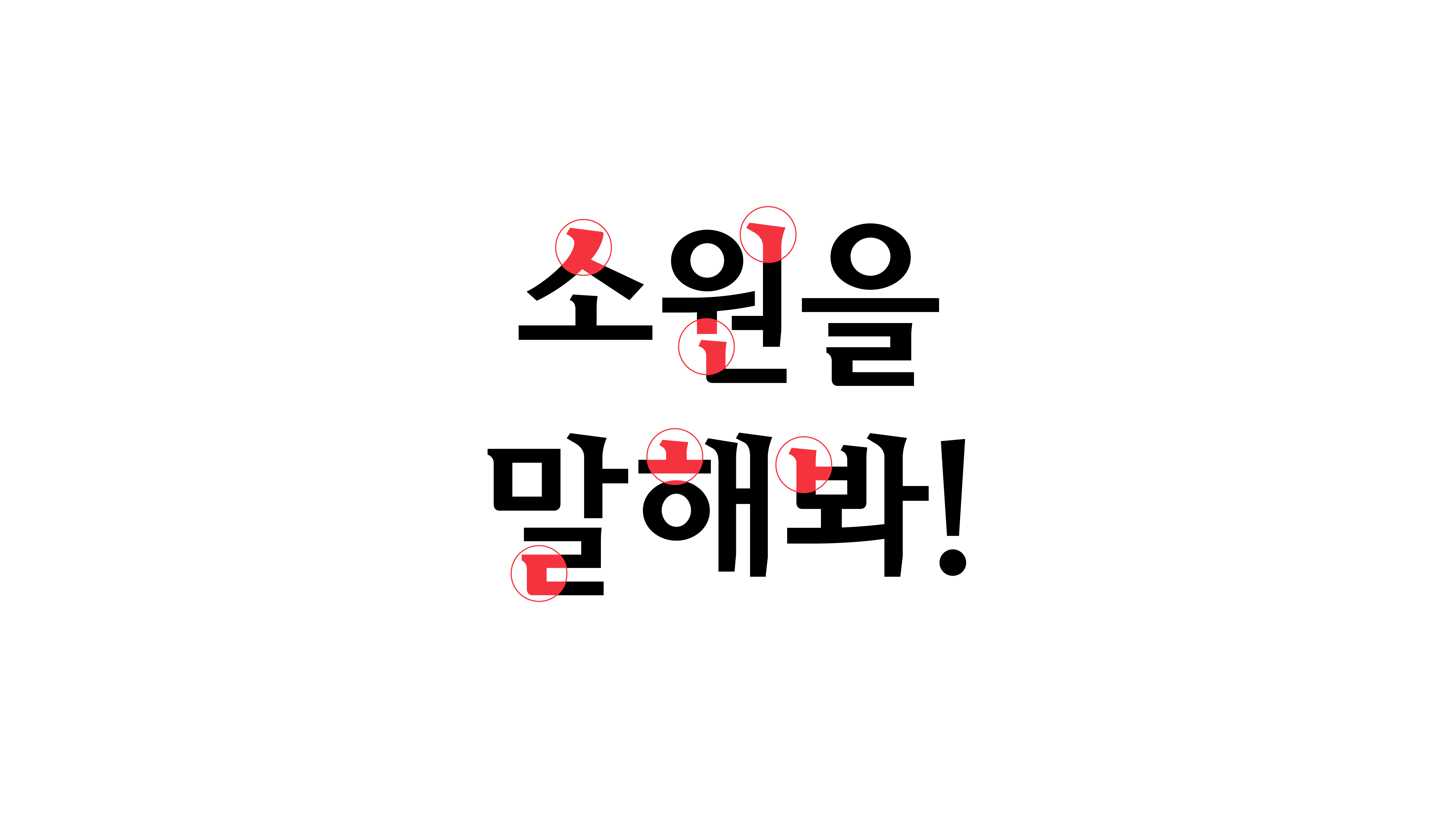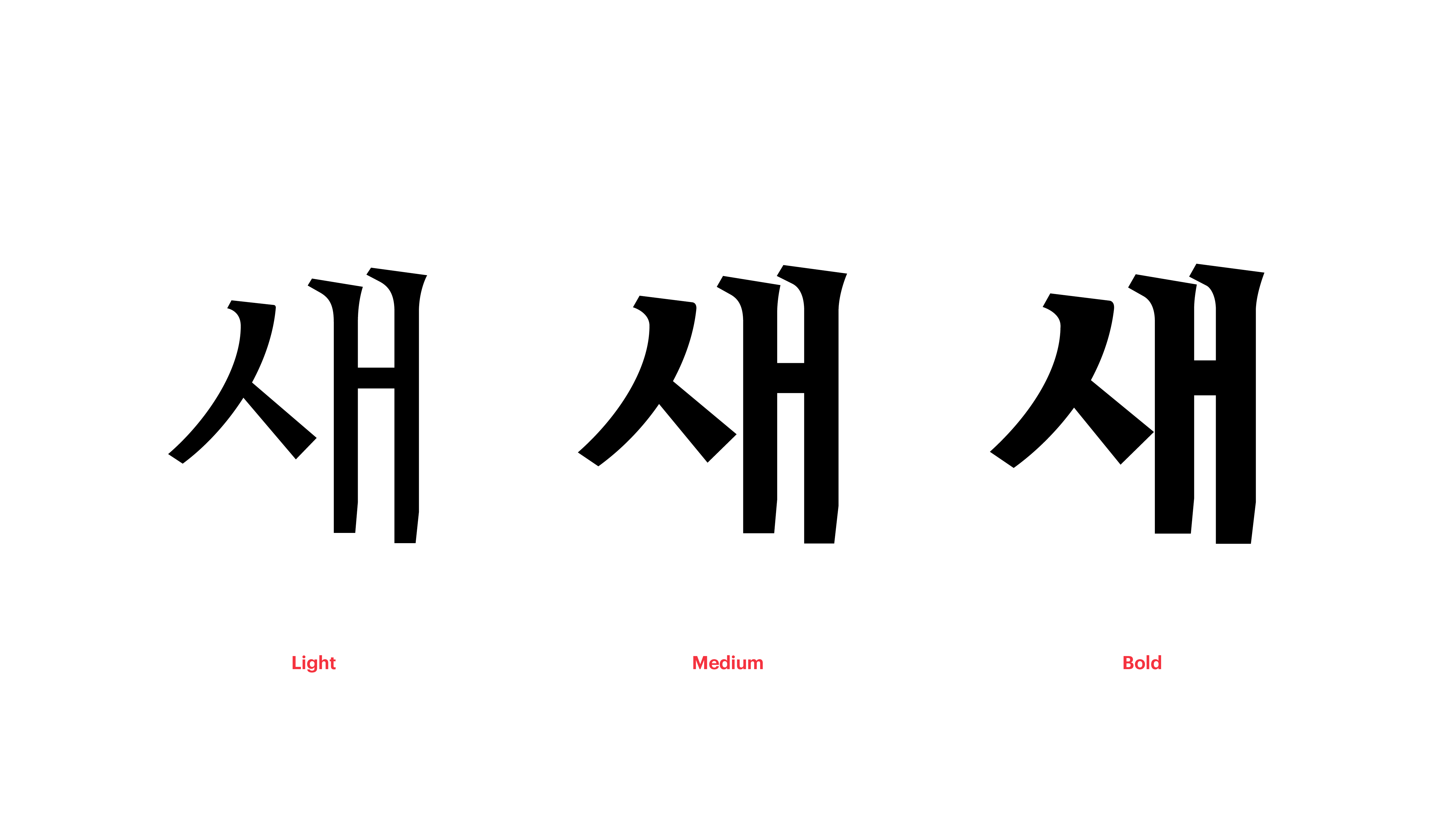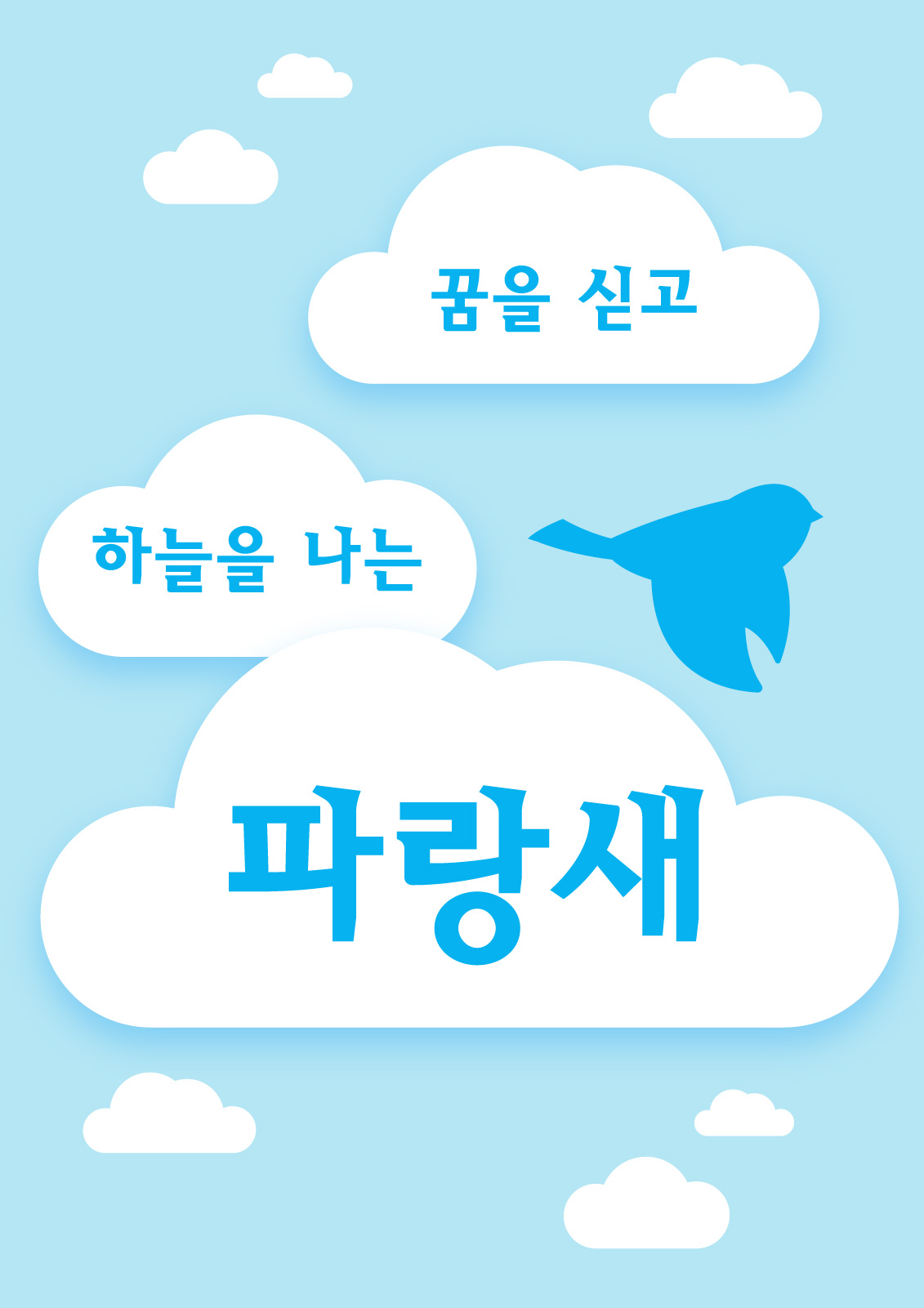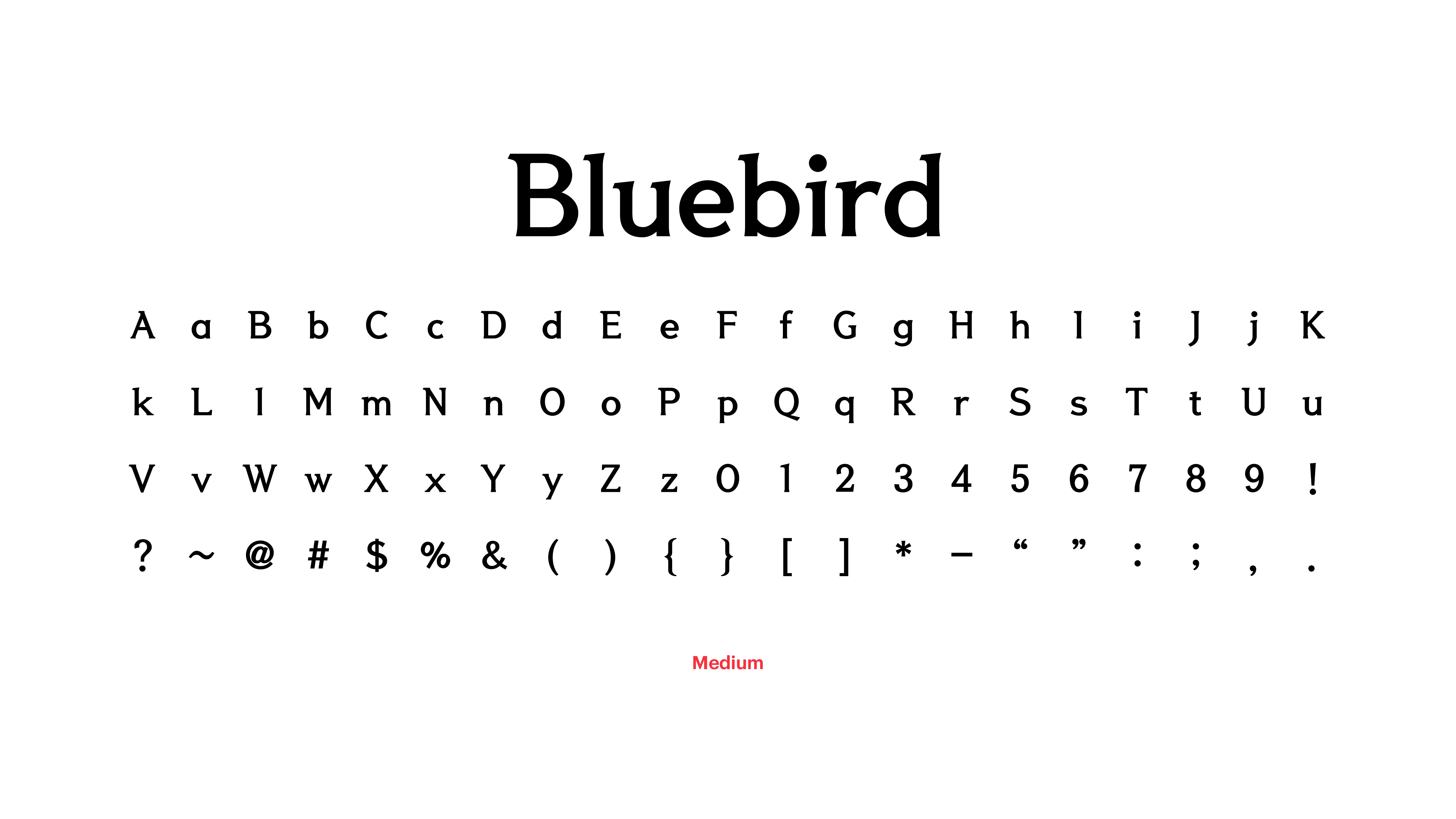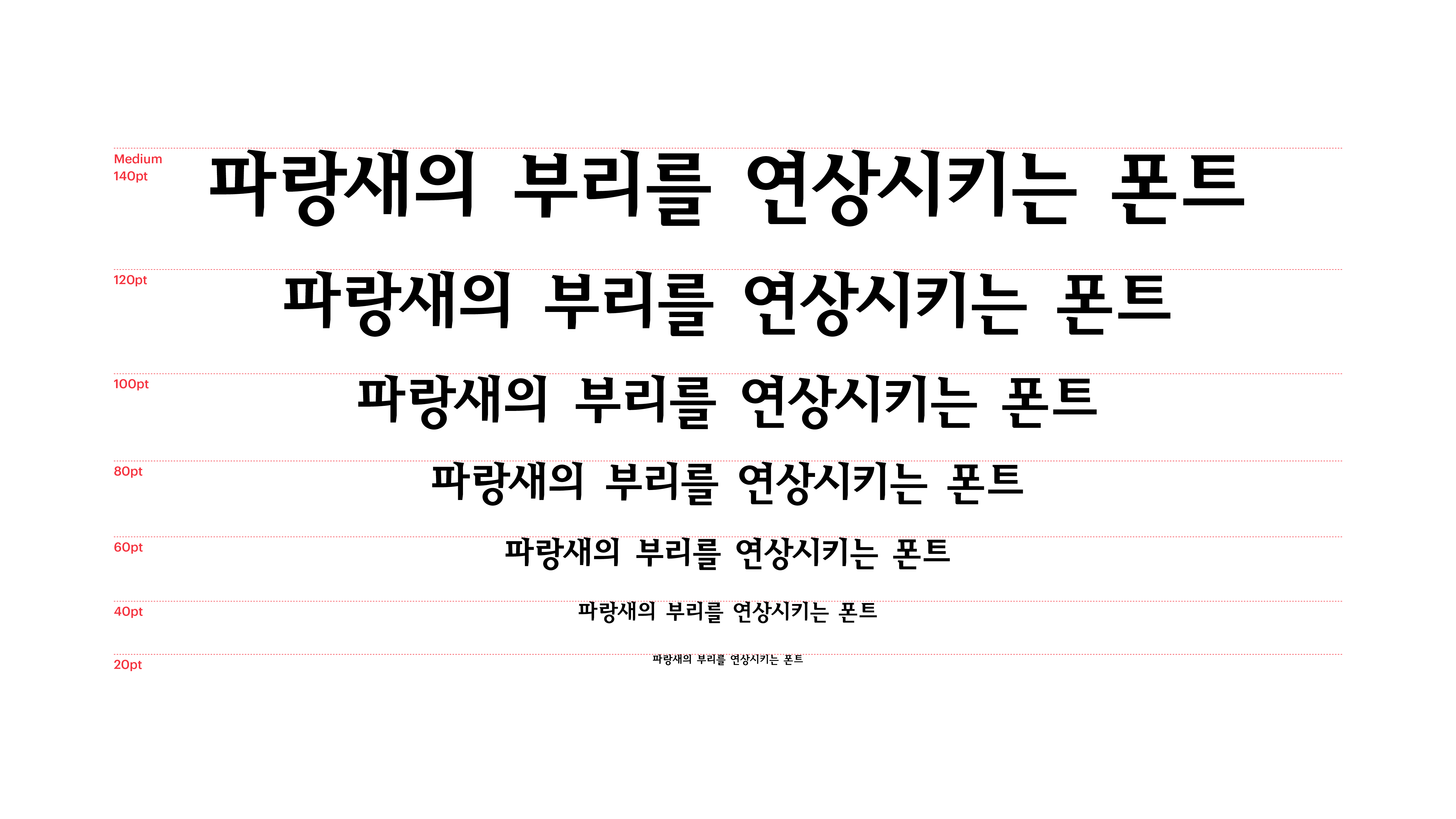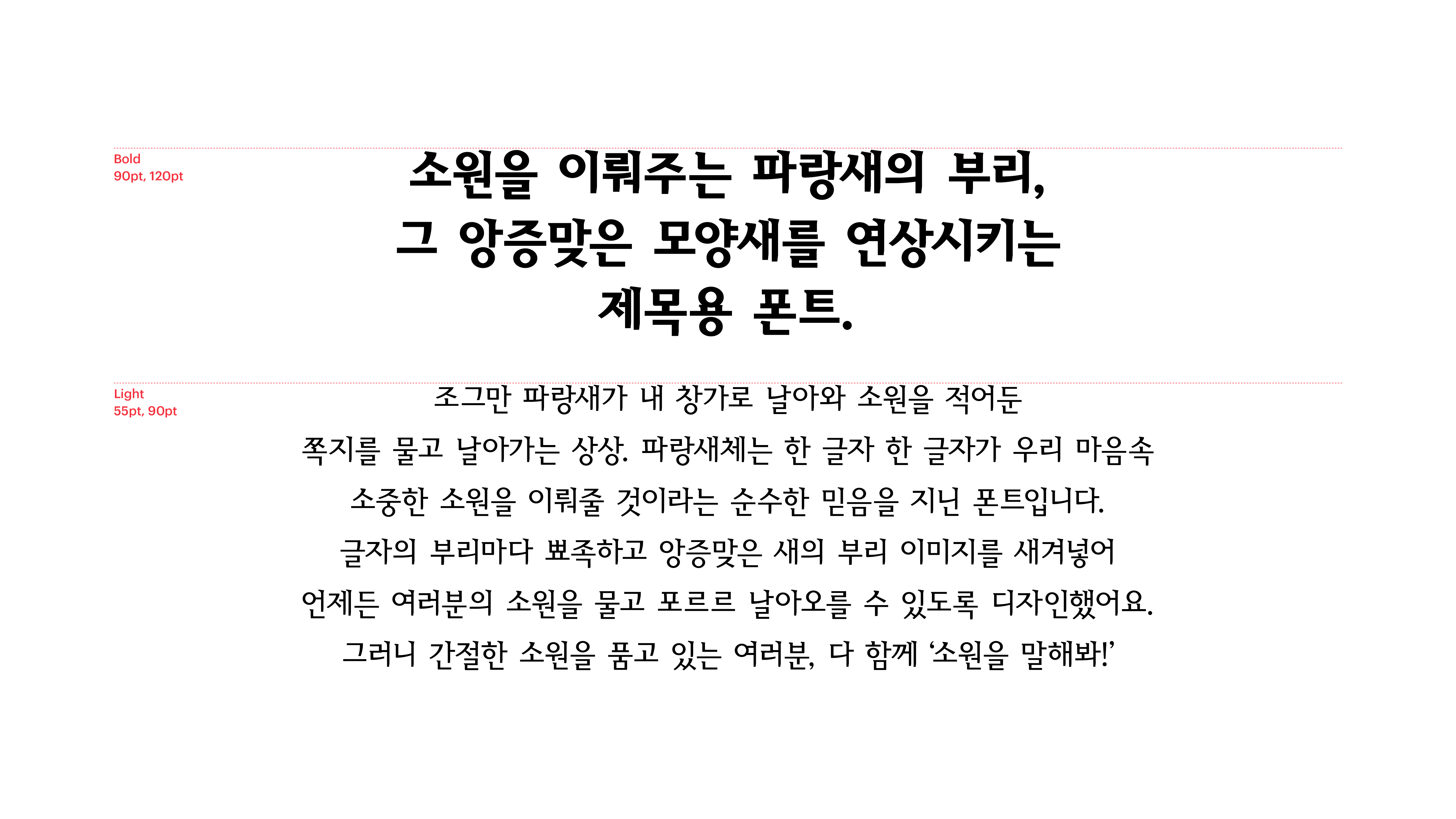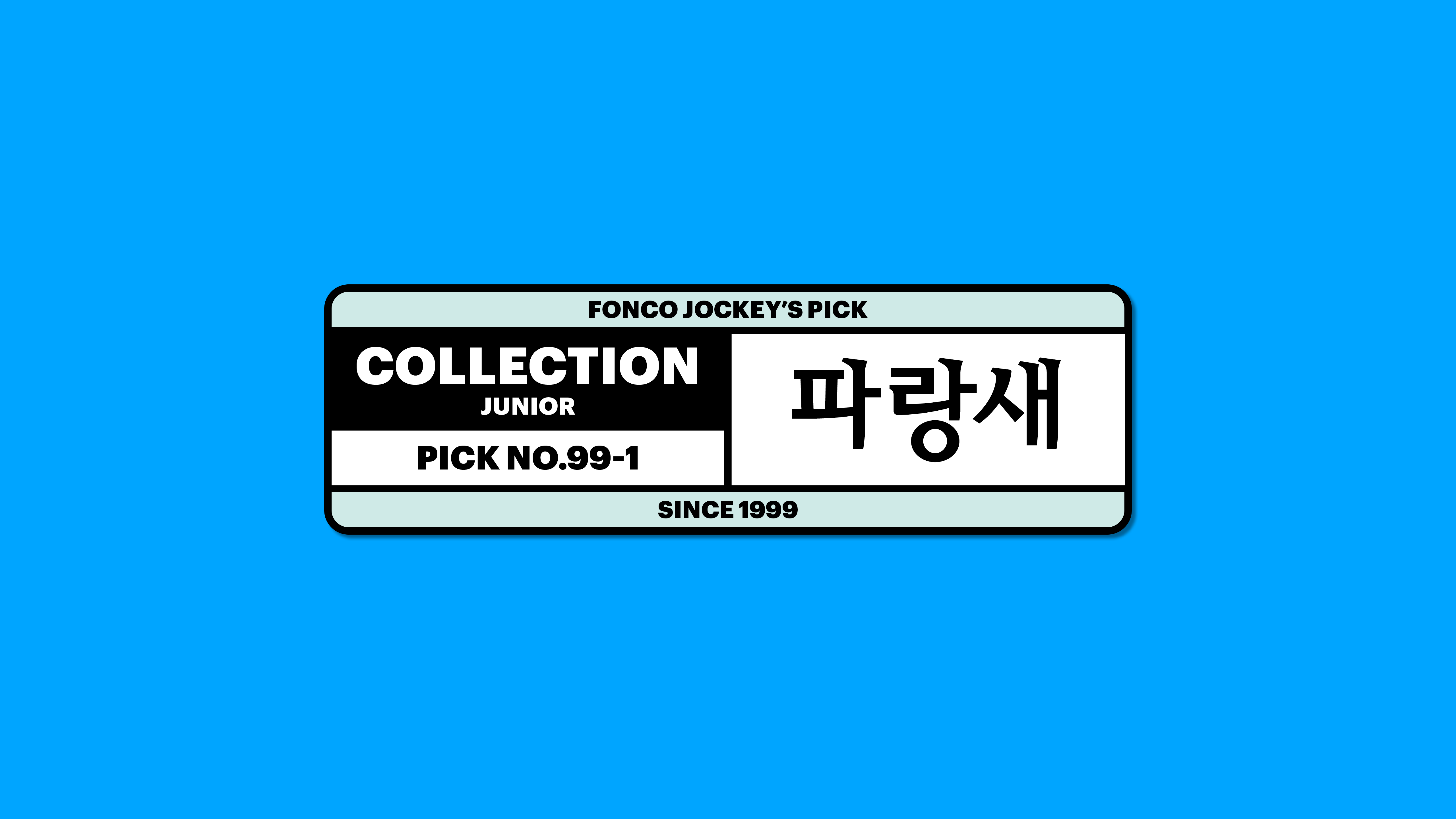
Yoon 파랑새
조그만 파랑새가 내 창가로 날아와 소원을 적어 둔 쪽지를 물고 날아가는 상상. 파랑새체는 한 글자 한 글자가 우리 마음속 소중한 소원을 이뤄줄 것이라는 순수한 믿음을 지닌 폰트입니다. 글자의 부리마다 뾰족하고 앙증맞은 새의 부리 이미지를 새겨넣어 언제든 여러분의 소원을 물고 포르르 날아오를 수 있도록 디자인했어요. 그러니 간절한 소원을 품고 있는 여러분, 다 함께 ‘소원을 말해봐!’